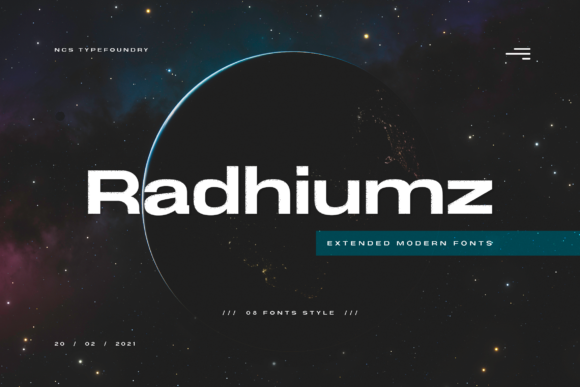
Creativefabrica Radhiumz Font
[Creativefabrica] Radhiumz Font
Радхийумз - минимальный и аккуратный шрифт без засечек.
Его легко подогнать под невероятно большой набор проектов, так что добавьте его к вашим творческим идеям и заметьте, как он выделяет их на фоне других!